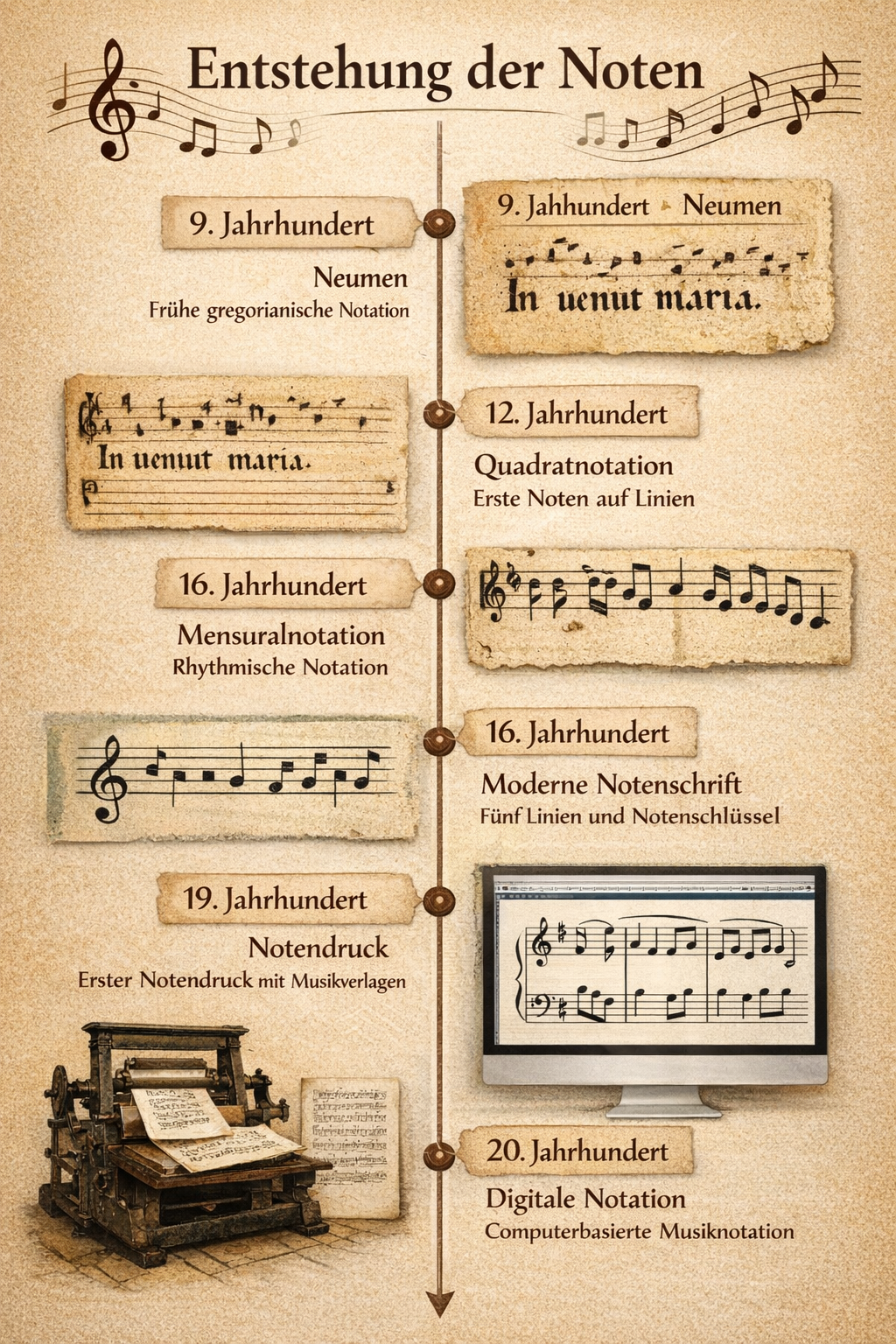
Notenschrift hat zwei Aufgaben: Sie zeigt den Klang (welche Töne) und den Rhythmus (wie lang, wie schnell). Beides wurde im Lauf der Jahrhunderte immer feiner aufgeschrieben — von den ersten Andeutungen über dem Text bis hin zum komplexen modernen Liniensystem.
Noten
Auch Musik wird geschrieben — und das schon seit über tausend Jahren. Aus den frühen Neumen mittelalterlicher Klöster entwickelten sich die Quadratnotation und schließlich die modernen Noten, mit denen wir heute Symphonien lesen.
Von Neumen zu modernen Noten
Die Entwicklung der Notenschrift